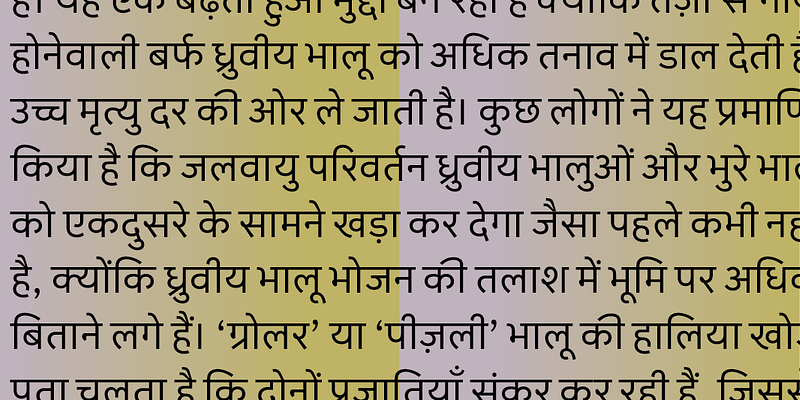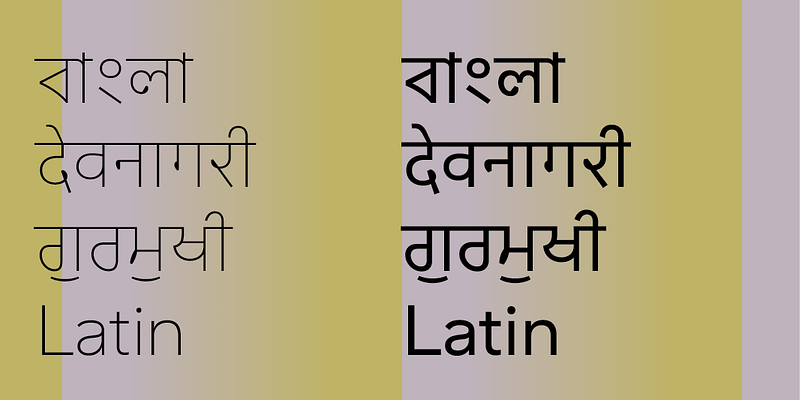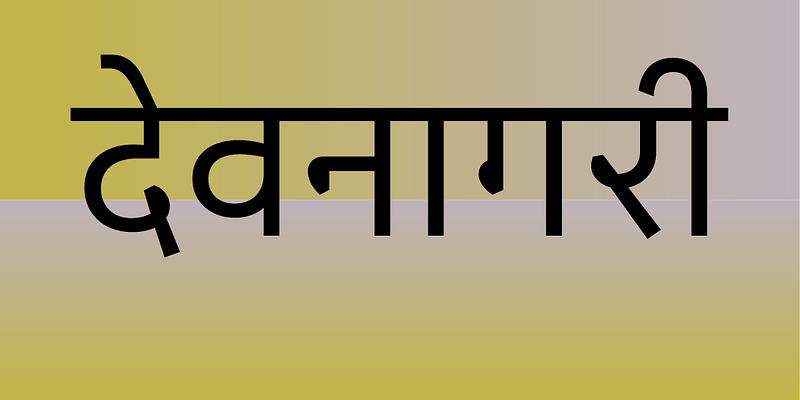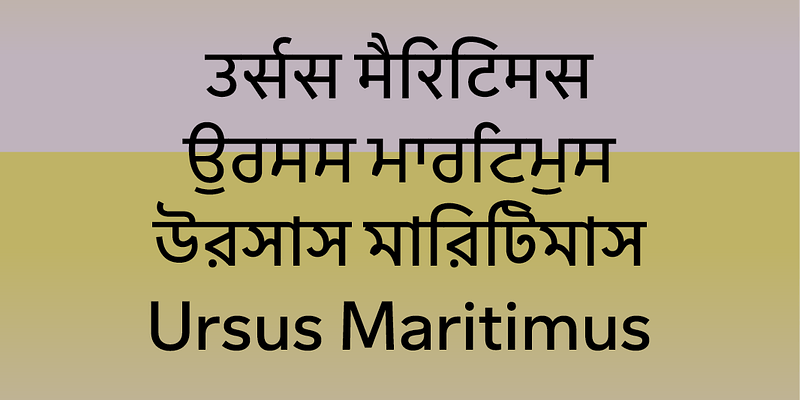
Sarvatrik은 벵골어, Devanagari, 구르무키어 및 라틴어 전반에 걸쳐 강력한 두께 세트와 언어 지원을 제공하며 추후에 더 많은 인도어 스크립트가 추가될 예정입니다. 크고 작은 크기 모두에서 잘 어울리지만 결코 친숙하고 개방적인 개성을 잃지 않는 실용적인 선택입니다. 라틴어 버전은 벵골어, Devanagari 및 구르무키어와 원활하게 작동하므로 다국어 브랜딩 또는 여러 시장에서 활동하는 회사에 적합합니다.
Universal Thirst는 인도어 및 라틴어 스크립트를 전문으로 다루는 서체 개발업체입니다. 디자이너이자 엔지니어인 Gunnar Vilhjálmsson과 Kalapi Gajjar가 2016년에 설립한 이 브랜드는 대조적인 시각적 유산을 활용하여 서체에 대한 독특하고 이중적인 관점을 제공합니다.